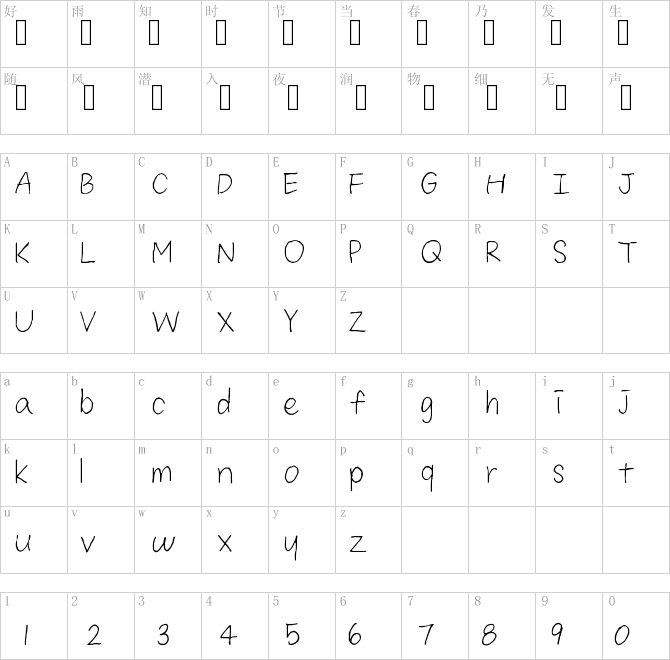
나눔손글씨 몽돌韩国字体
나눔손글씨 몽돌韩国字体,这款字体结构工整、笔画清晰,兼顾美观与易读性,适用于标题、正文、海报、包装、LOGO 等多种场景。字形优雅稳定,风格百搭耐看,适配日常排版与创意设计,让文字呈现更舒适、更具质感。나눔손글씨 몽돌韩国字体一笔一画,皆是细节,以均衡的比例、流畅的线条打造舒适视觉体验,字形端正大气,风格简约现代。无论是商业设计、品牌宣传还是日常排版,都能轻松驾驭,让文字更有格调与力量。나눔손글씨 몽돌韩国字体字体下载。